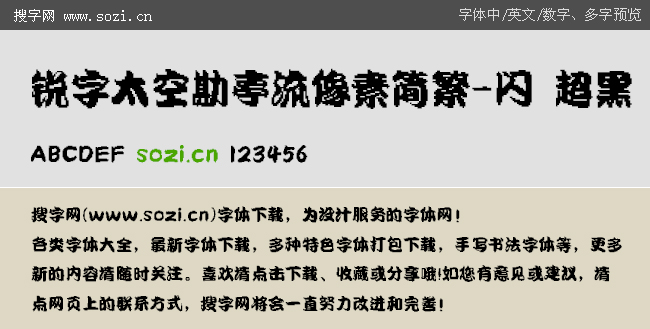
锐字太空勘亭流像素简繁-闪 超黑
搜字网提供一款锐字太空勘亭流像素简繁-闪 超黑中文字体下载,锐字太空勘亭流像素简繁-闪 超黑是一款艺术字体,华丽的日式字体,加入像素特征,增添了动感与游戏感。适合用于标题设计、海报设计、包装设计等场景广泛应用。(本字体为个人非商用版,商用请联系作者购买授权。官方网址:http://www.reeji.com 联系方式:021-58597892)